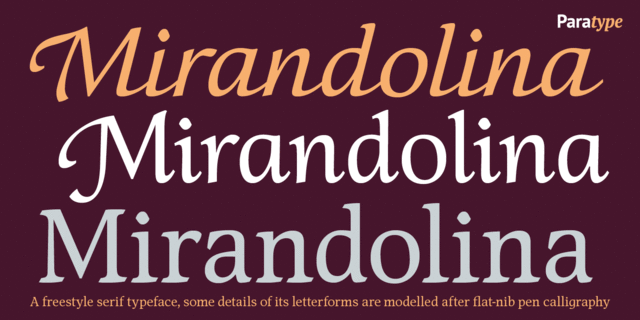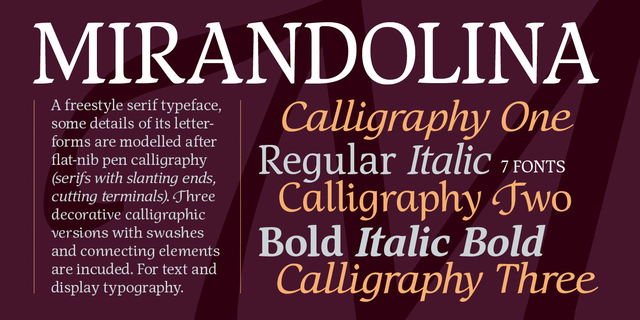
Mirandolina (7 шрифтів)
Антиква, детали рисунка которой имитируют некоторые особенности каллиграфии широким пером (скошенные засечки, «срезанные» концевые элементы). Имеет декоративные каллиграфические версии с росчерками и соединительными элементами, отличающиеся теми же особенностями формы. Предназначен для текстового набора и акциденции. Шрифт спроектирован Натальей Васильевой и лицензирован компанией ПараТайп в 2007 году.